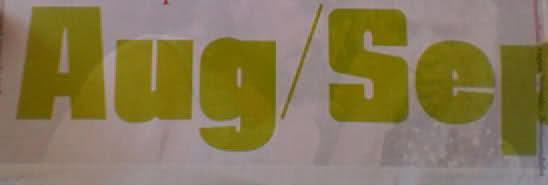
ich hab auch keine ahnung. schaut ziemich alt aus. aber wenn’s was ähnliches, allerdings neues sein soll: die bumper
DNOICD+Architect2009                 Type 1C           yes yes no     225  0
DNOICE+AvenirNextLTPro-Demi          Type 1C           yes yes yes    237  0
DNOIDG+AvenirNextLTPro-Medium        Type 1C           yes yes yes    239  0
DNOIDH+TimesNewRomanPS-ItalicMT      Type 1C           yes yes yes    248  0
DNOIEJ+MinionNeue-Bold               Type 1C           yes yes yes    243  0
DNOIFK+MinionNeue-VersalRegular      Type 1C           yes yes yes    232  0
DNOIFL+MinionNeue-BoldItalic         Type 1C           yes yes yes    249  0
DNOIGN+MinionNeue-RegularItalic      Type 1C           yes yes yes    226  0
DNOIHP+MinionNeue-Regular            Type 1C           yes yes yes    217  0
DNOIIA+MinionNeue-Semibold           Type 1C           yes yes yes    244  0
DNONNI+Middleton+KDNQLH              Type 1C           yes yes yes    189  0
DNONNJ+Helvetica-Black+FEJDZK        Type 1C           yes yes yes    195  0
DNPDLH+MetroflexUni-Bd+BMYQCL        Type 1C           yes yes yes    174  0
DNPDMJ+MetroflexUni-Lt+XJRGNT        Type 1C           yes yes yes    201  0
DNPHEO+Zeichen-Eins                  Type 1C           yes yes yes    199  0
DNPPDA+DSH-Dingbats                  Type 1C           yes yes yes    170  0
DNONIE+Helvetica-Light+FOZEPD        Type 1C           yes yes yes    182  0